دانلود Handwritten 80 Fonts Collection مجموعه فونت دستنویس انگلیسی
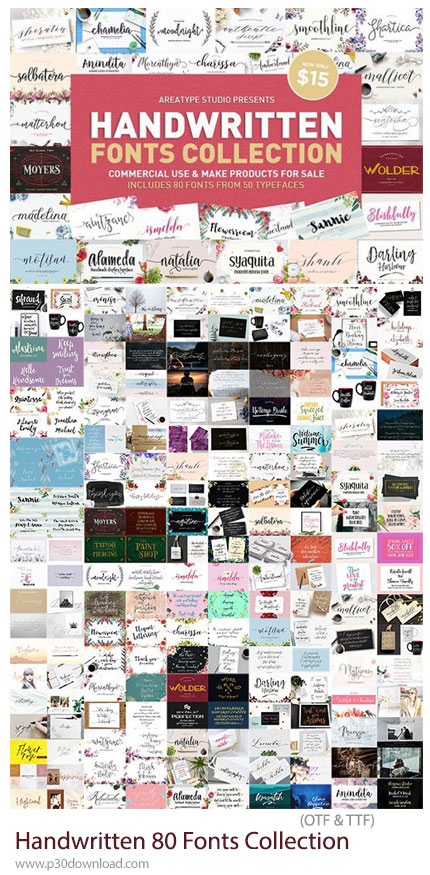
این مجموعه یک پکیج ارزشمند و حرفهای از فونتهای دستنویس است که با دقت بالا طراحی شدهاند تا ظاهری گرم، انسانی و خلاقانه به پروژههای شما بدهند که با فرمت های OTF و TTF بر روی سایت برای دانلود قرار گرفته است. این مجموعه شامل 80 فونت متفاوت با سبکهای گوناگون دستخط است؛ از دستخطهای کلاسیک و مینیمال گرفته تا فونتهای فانتزی، هنری و مدرن. این پکیج انتخابی عالی برای طراحان گرافیک، تولیدکنندگان محتوا، طراحان برند، و هر کسی است که میخواهد به پروژههای خود حس شخصیسازی و جذابیت بصری بیشتری بدهد.